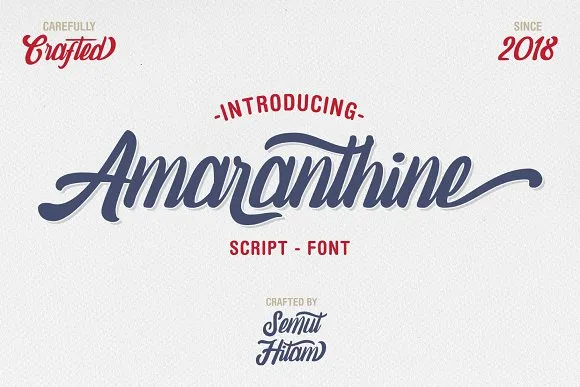
Amaranthine Script Font – Download Grátis
Amaranthine Script Font é uma elegante fonte cíntica vintage para aqueles que buscam adicionar um toque sofisticado a seus designs. Inspirada nos estilos dos anos 50, essa fonte suave e nostálgica será uma perfeita escolha para personalizar seu logotipo de empresa ou marca, criar convites, cartazes de eventos, capas de livros, mensagens de aniversário, citações e muito mais. Com um conjunto completo de caracteres opentype, incluindo letras maiúsculas e minúsculas padrão, pontuação e numerais, além de suporte multilíngue, ligações, alternativas estilizadas e um amplo leque de outros ícones, Amaranthine Script Font é perfeitamente adequada para uso pessoal e comercial. Este design cuidadosamente criado e compartilhado pelo designer junART traz uma experiência visual única e impressionante a qualquer projeto.